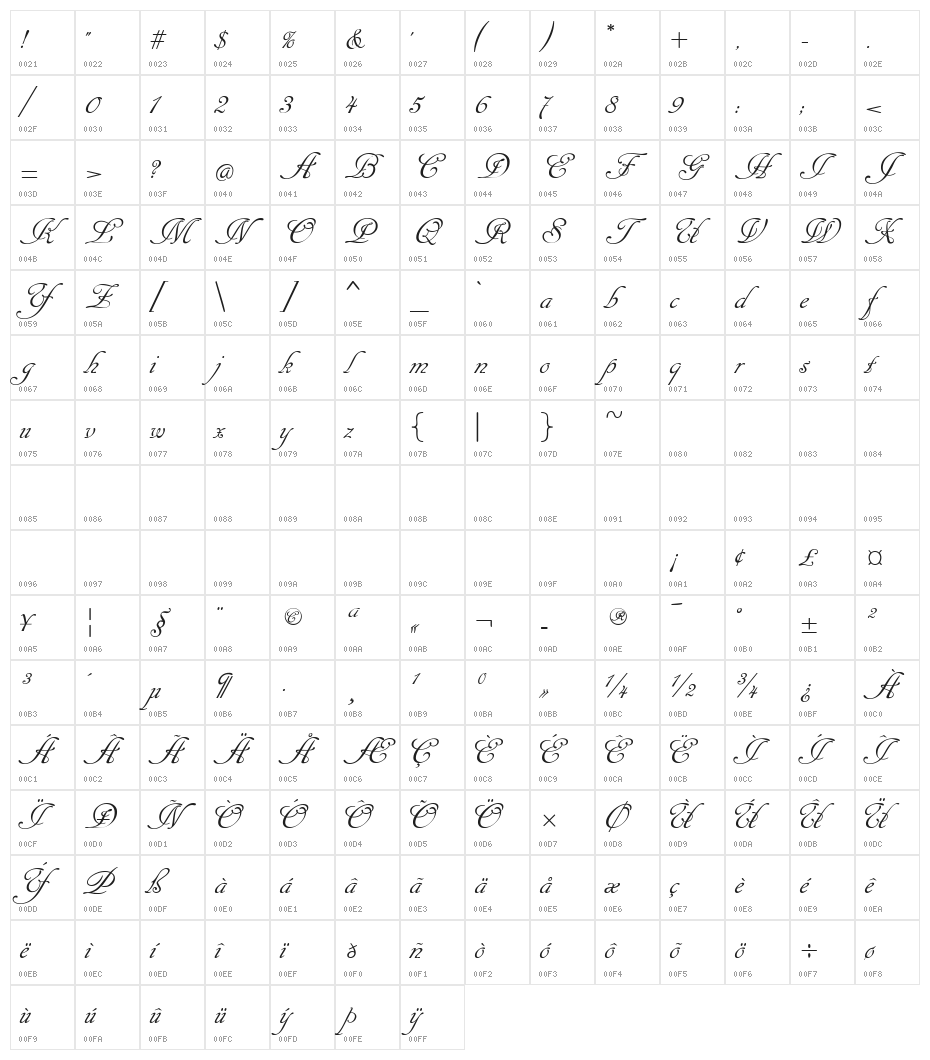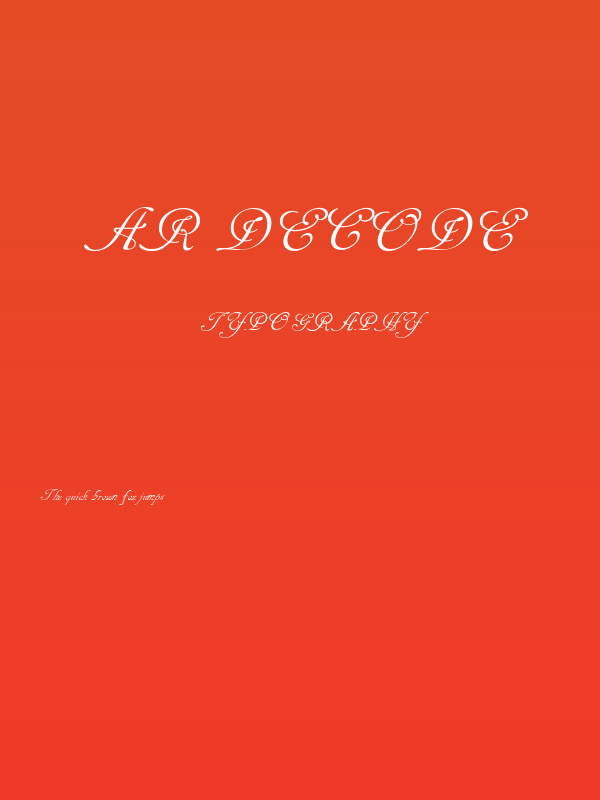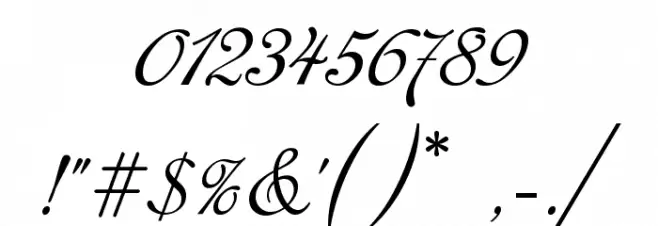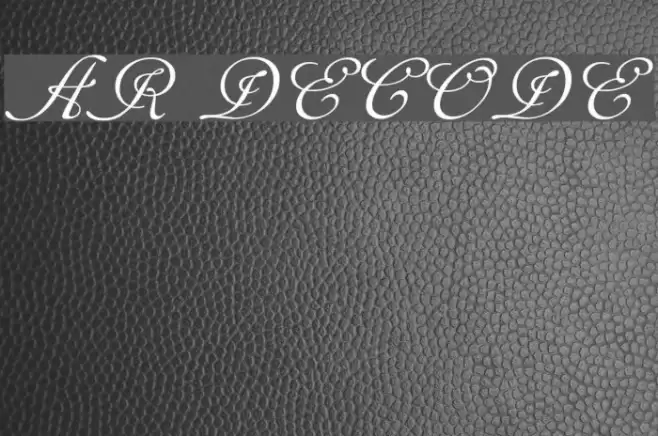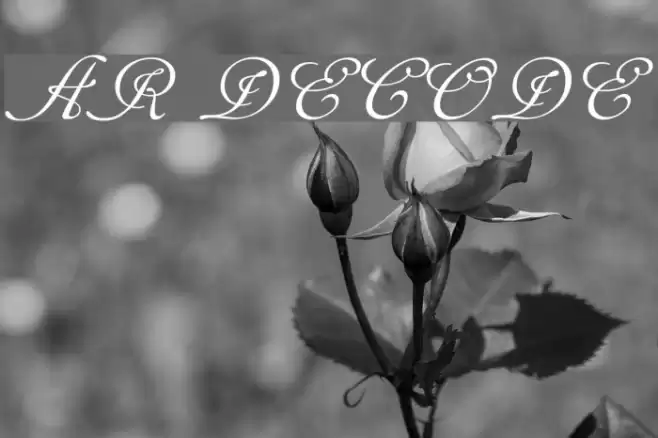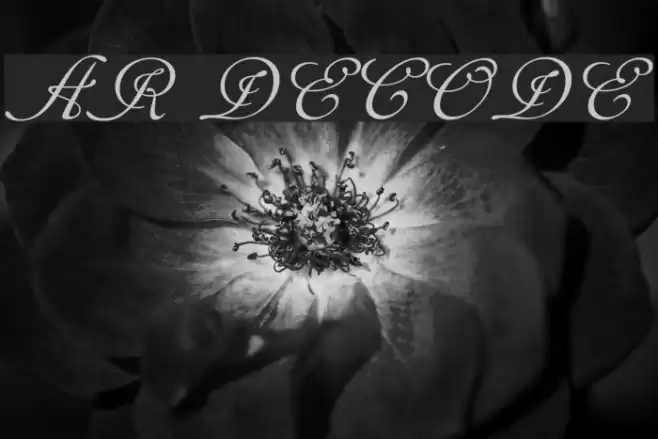
AR DECODE Font
✎ Script
| Категория | Script |
| Общий стиль | Classic |
| Область применения | Logos, Invitations, Branding |
| Рекомендуемые проекты | Ideal for wedding invitations, luxury branding, elegant signage, and formal event programs. |